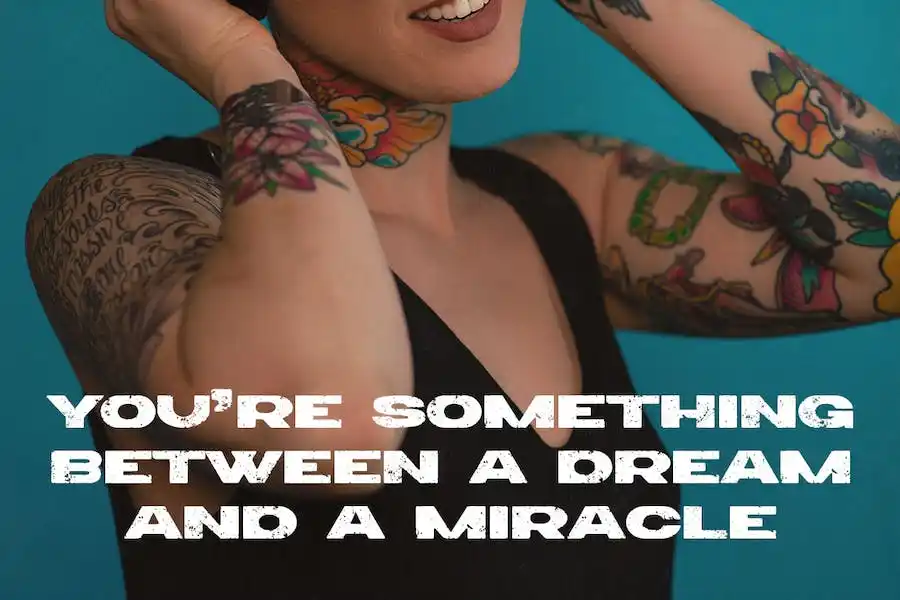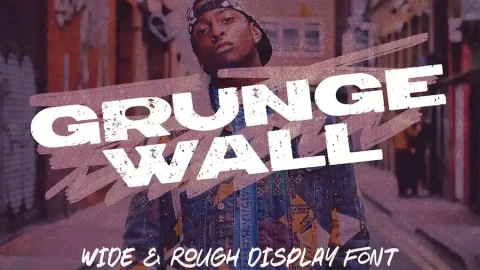
grunge Wall Wide là phông chữ sans serif rộng, thô, cổ điển, táo bạo và mang phong cách thành thị dành cho các dự án mới của bạn. Với sự hỗ trợ đa ngôn ngữ và phong cách đường phố retro & grunge 😉